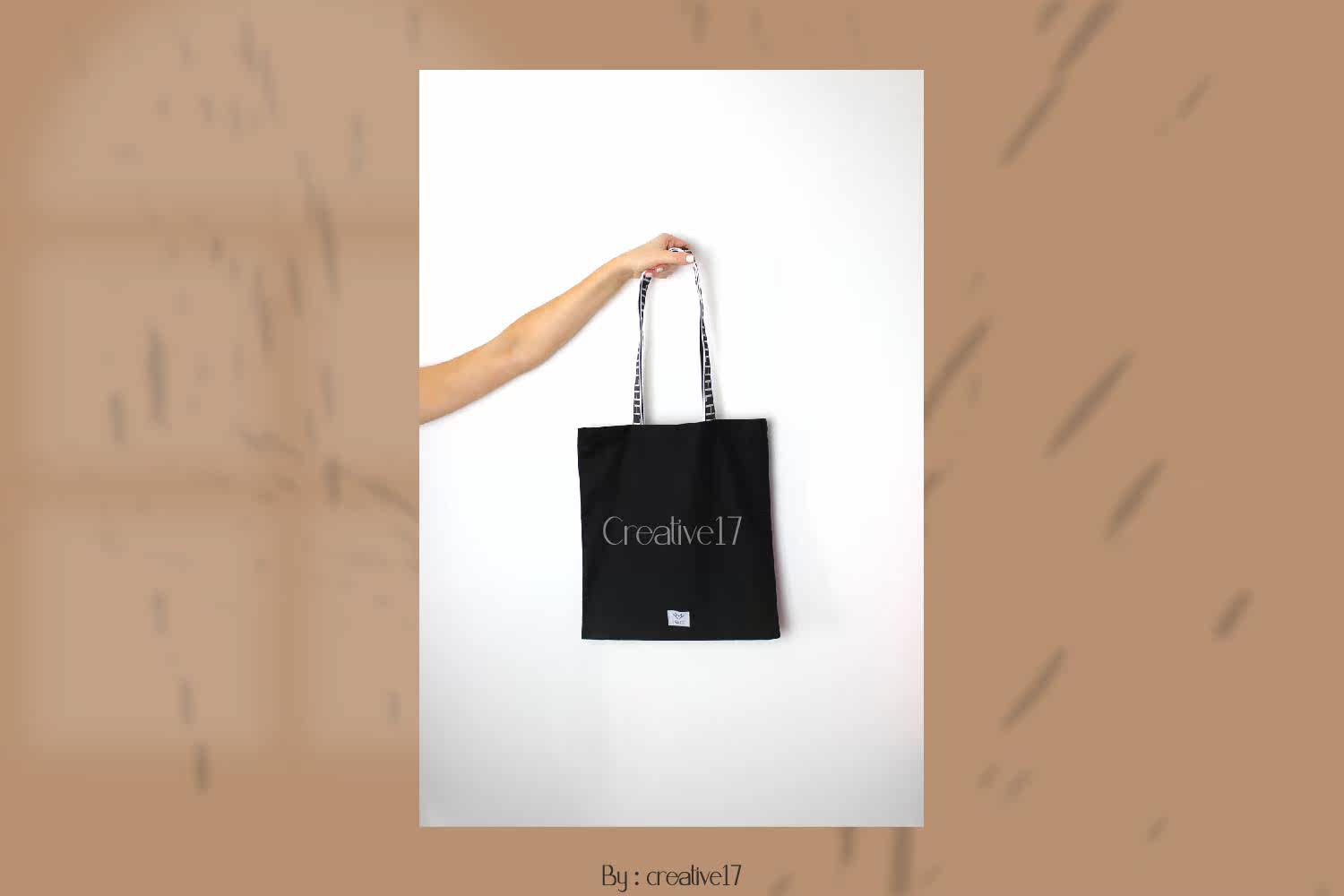
责怪Banganisastyl删除ModernInfo,此字体适用于大型和小型项目,如品牌、婚礼宣传卡、徽标以及其他设计项目。此字体责怪Banganistyl包括完整集、大写、小写、数字、标点符号、多语言支持以及其他连字和替代字母。责怪Banganisastyl删除ModernInfo,此字体适用于大型和小型项目,如品牌、婚礼宣传卡、徽标以及其他设计项目。此字体包括完整集、大写、小写、数字、标点符号、多语言支持以及其他连字和可选字母。